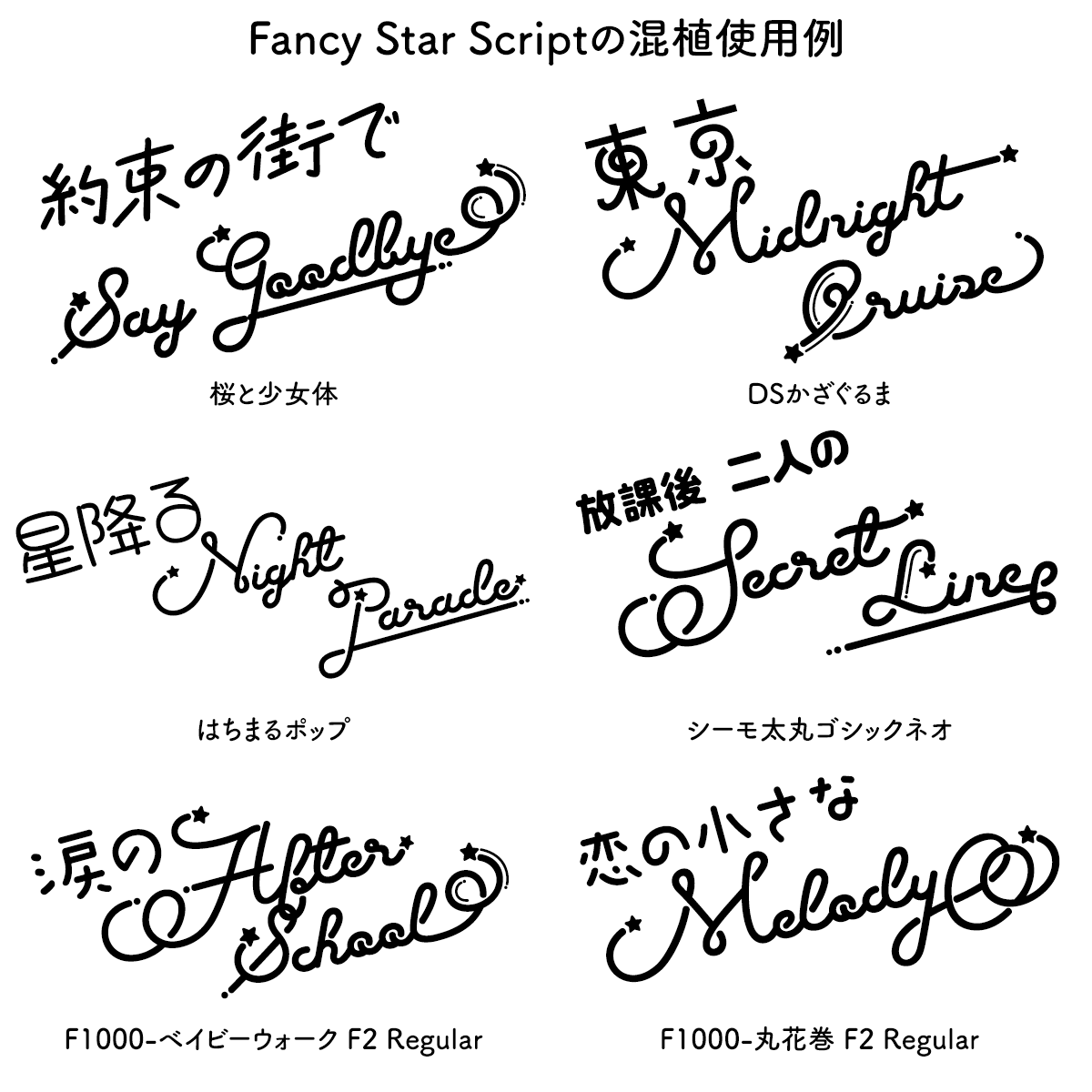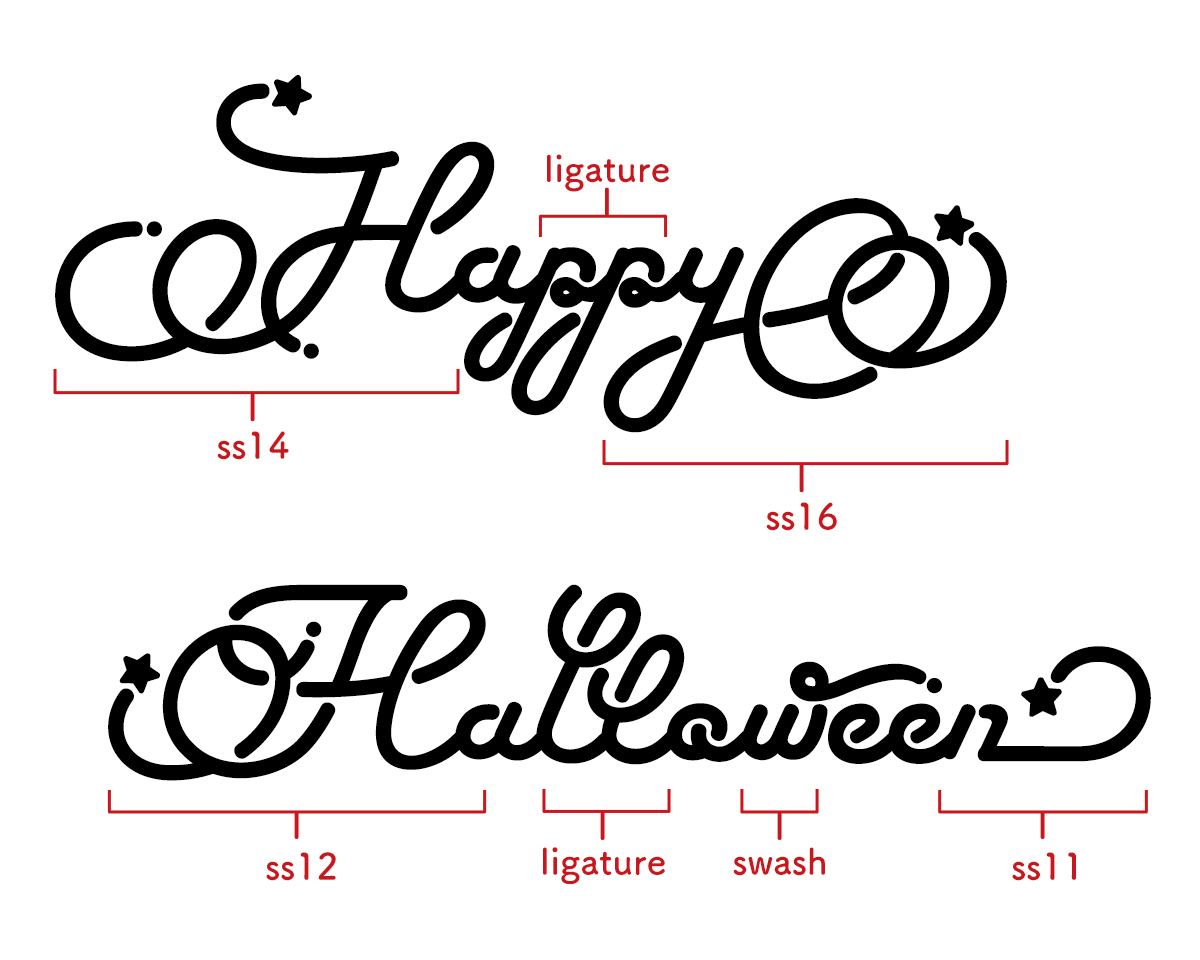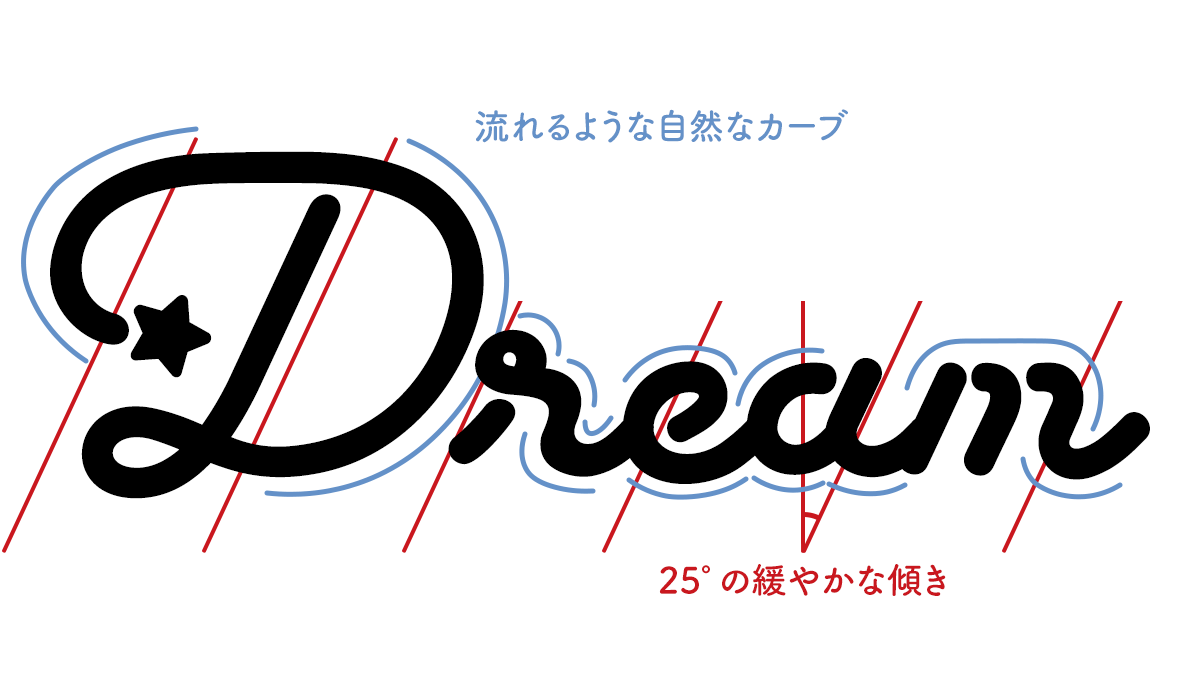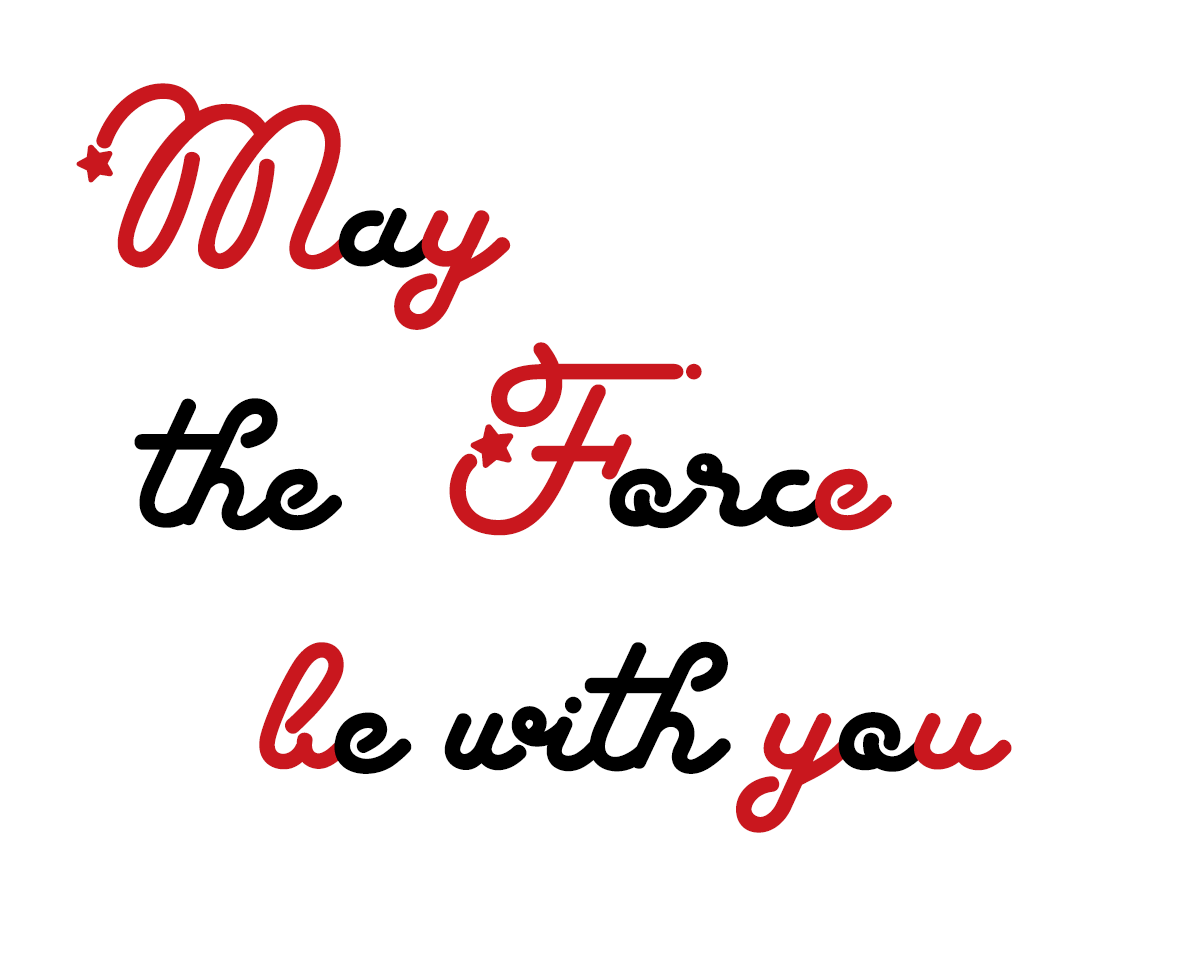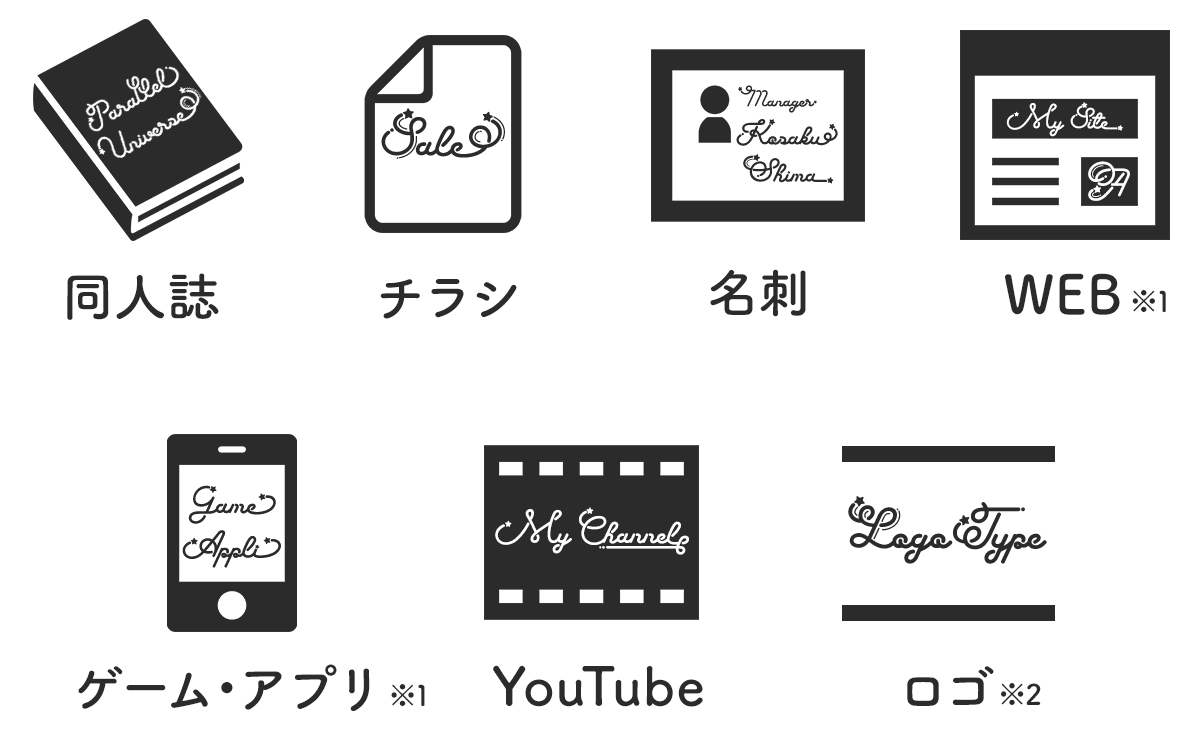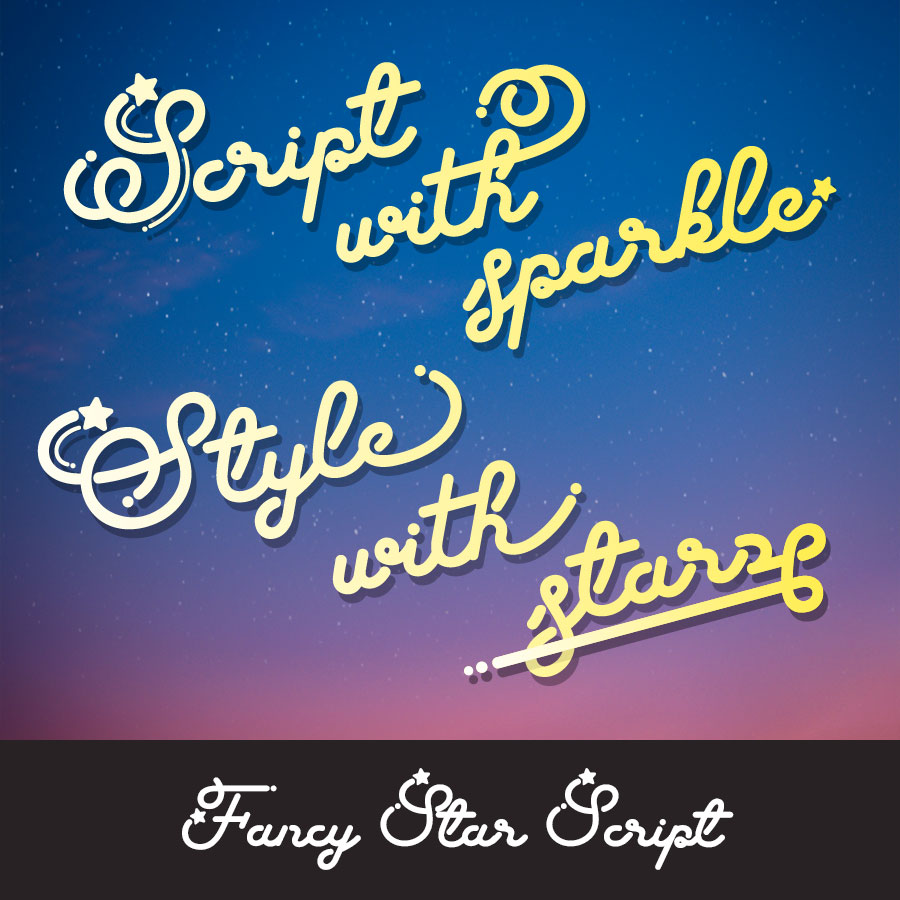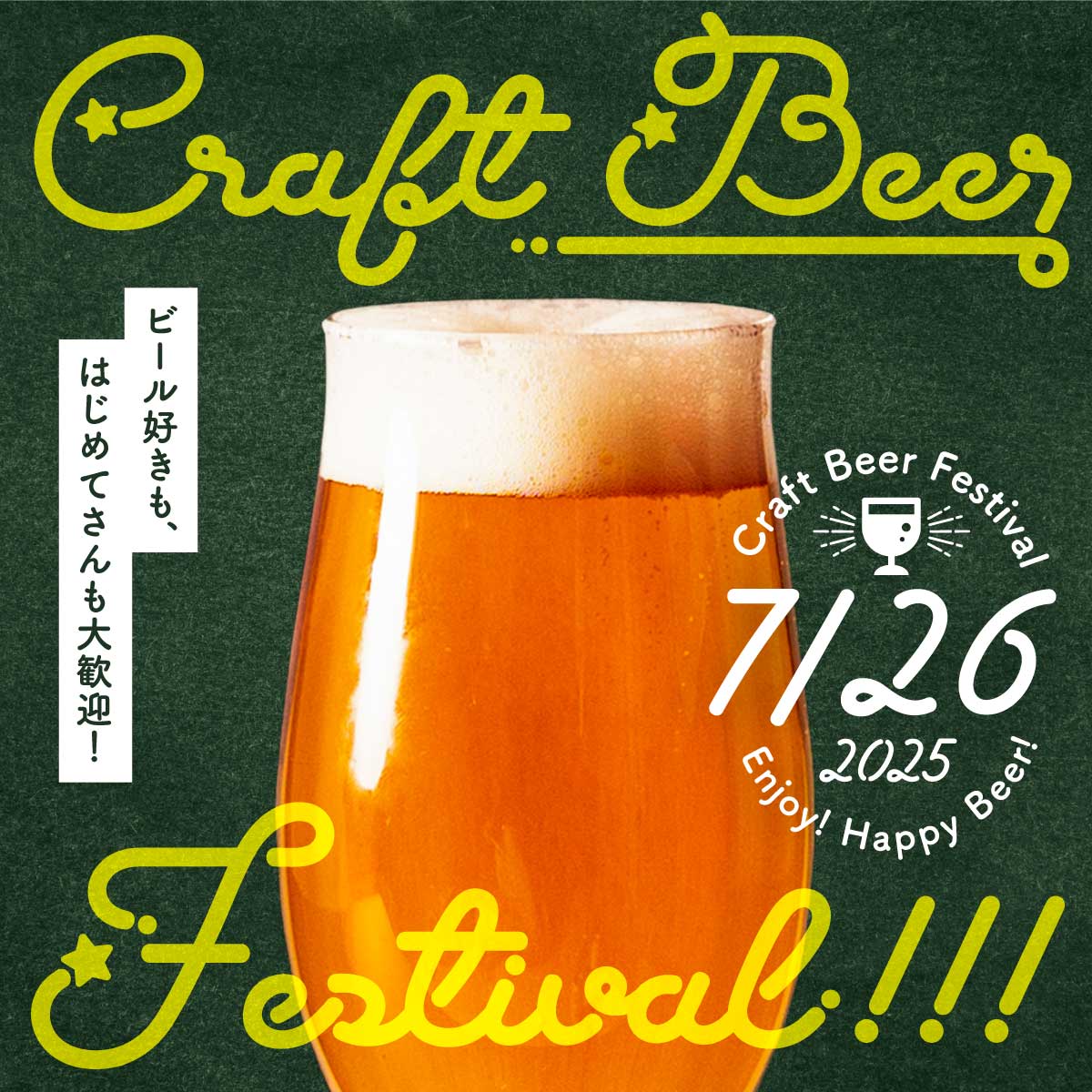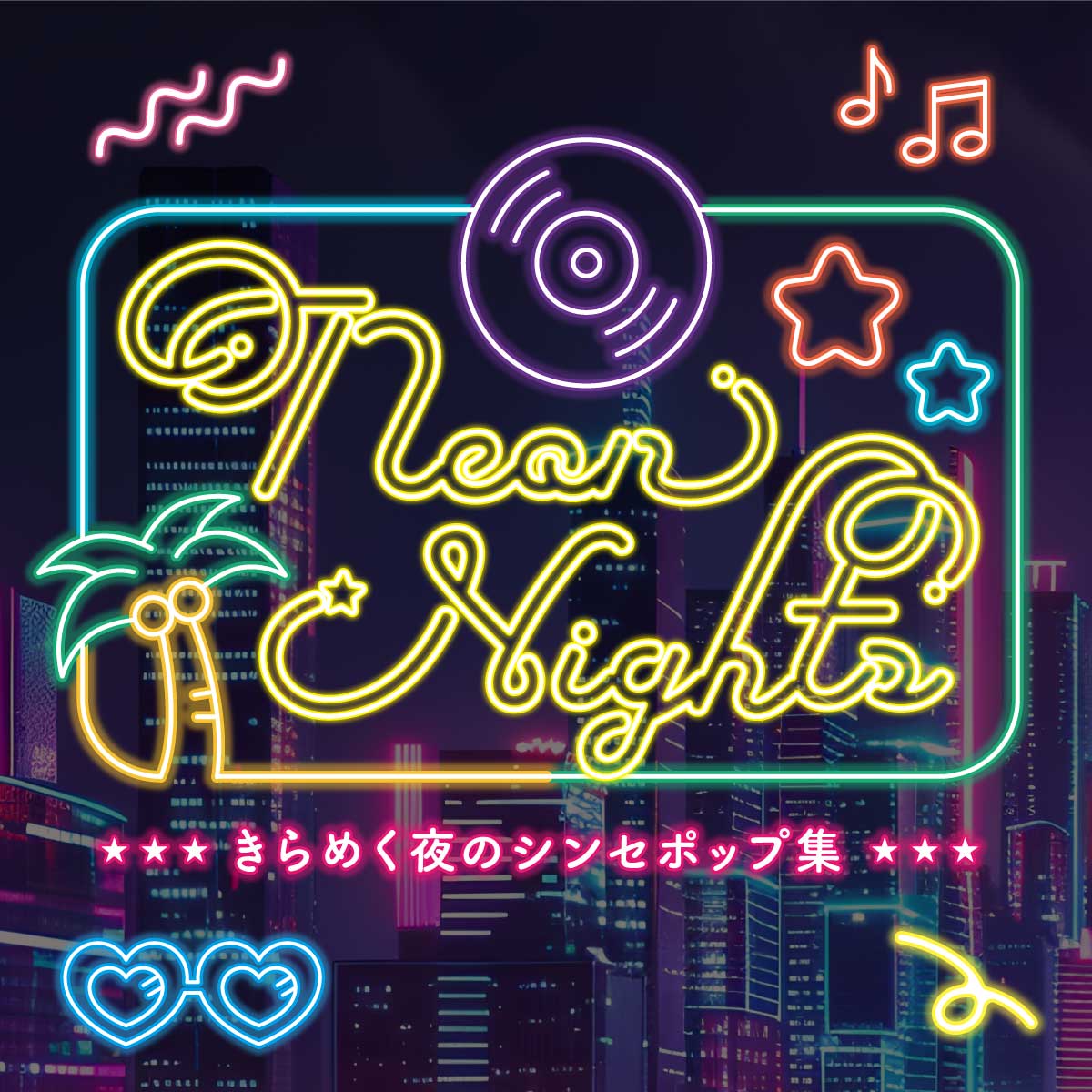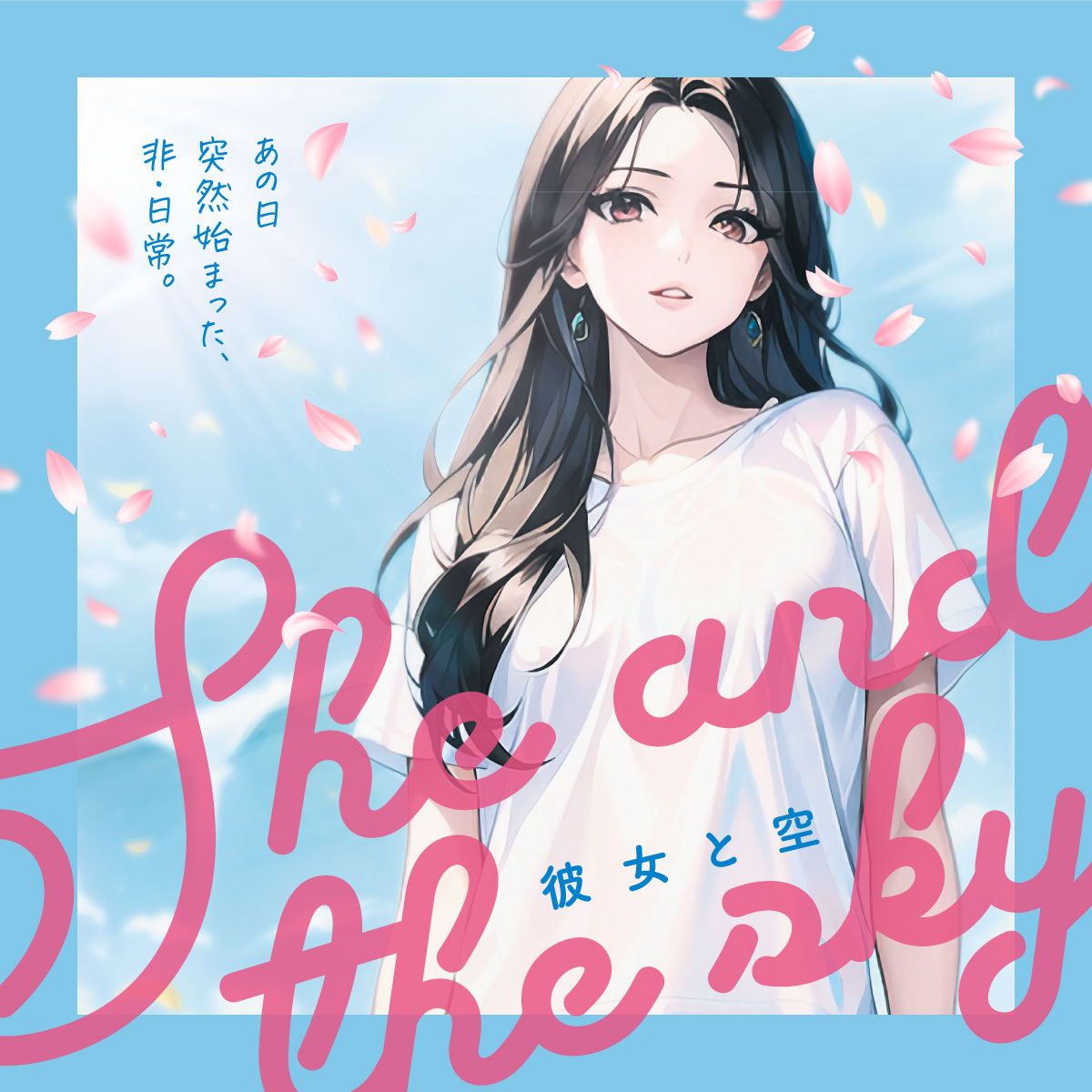
Fancy Star Script シティポップでレトロな筆記体、スクリプト体
シティポップな雰囲気をつくれる筆記体フォント Fancy Star Script|異体字17種類収録
雰囲気のあるデザインを手軽につくりたいときに役立つ筆記体フォントが Fancy Star Script。レトロでポップな印象を持ちつつ、17種類の異体字(異なる文字デザイン)を使い分けることで、ひとつの言葉にもさまざまなニュアンスを加えることができます。
Illustrator や Photoshop では、文字を入力したあとに簡単に異体字へ切り替えることが可能です。また、異体字の切り替え機能がないソフトでも、異体字ごとに用意されたファイルを選ぶだけで使えるので安心です。
ロゴやZINE、MVのタイトルなど、雰囲気を大切にしたい場面にフィットするフォントです。デザインに遊び心を添える、ちょっと特別なスクリプト体。Fancy Star Script、きっとあなたも好きになります。
「Fancy Star Script」の概要
Fancy Star Script
シティポップでレトロな筆記体、スクリプト体 Fancy Star Script サンプル  シティポップでレトロな筆記体、スクリプト体 Fancy Star Script サンプル
「Fancy Star Script」とは?
文字って、もっと自由でいい ──「Fancy Star Script」に込めた遊び心とときめき
シティポップでレトロな筆記体、スクリプト体 Fancy Star Scriptの制作者 渋谷瞳さん
子どもの頃のロゴ遊びから始まり、手書きの温かさとデジタルの設計を融合させて独自のフォントを生み出してきたタイプデザイナー・satsuyakoさん。
そんな彼女が手がけた「Fancy Star Script」は、ノスタルジックでポップ、そして自由なリズムを感じさせる筆記体フォントです。 星のようにきらめく文字たちは、手書きの楽しさと遊び心に満ちていて、ロゴやタイトルを「見る人の記憶に残す」力を秘めています。
この書体に込めた思いや制作背景、こだわりの設計、そして使う人に伝えたいメッセージを伺いました。
「こんなフォントがあったらいいな」という発想から生まれる、シンプルで少し遊び心のあるフォントが特徴。筆記体やピクセル風などジャンルは多彩で、代表作に「Fancy Star Script」や「Love Letter」などがある。
カリグラフィーの経験を活かした繊細なデザインと、日本人ならではの感性が織りなす作風は、多くのクリエイターに支持されている。SNSでは制作過程や使い方のヒントも発信中。
「文字って面白い」──遊び心から始まった、世界に届く文字づくり
シティポップでレトロな筆記体、スクリプト体 Fancy Star Scriptの作者 satsuyakoさんの創作のルーツ
フォントとの出会いは、子どもの頃の”ロゴ遊び”から
フォントに興味を持ち始めたのは、小学生の頃に好きなフォントを使ってロゴのようなものを作って遊んでいたことがきっかけでした。
画面の中で文字が持つ雰囲気や印象の違いに夢中になって、そのとき目に留まったフォントの存在はいまも記憶に残っています。
デザインの仕事を通して”つくる”楽しさに目覚めて
学生時代からデザイン制作会社の仕事に携わるようになり、当時は携帯電話向けの「デコメ」素材などの制作が主な業務でした。
その延長でドット系のフォントを作るようになり、漢字入りの日本語フォントがまだ少なかったこともあって、まずは自分の手書き風の文字で作ってみようと思ったのが、本格的にフォント制作をはじめたきっかけとなりました。
世界に届く文字づくりを目指して
その後、日本国内で配布・販売されている筆記体フォントの少なさにも気づき、欧文フォントの制作にも自然と関心が広がっていきました。
筆記体らしさを追求するなかで、カリグラフィーの歴史や書法も独学で少しずつ学びながら制作に取り組んでいます。
また、初期に制作した日本語フォントの一部が思いがけずGoogle Fontsに採用されたことをきっかけに、より多くの方に届けられる文字づくりを意識するようになりました。
フォントを制作する中で、先に道を切り拓いてこられた多くの書体や制作者の存在に触れるたび、その緻密さや美しさに心を動かされ、今も変わらず大きな刺激と励みをもらっています。
初期作から広がる世界──「自分の文字」をフォントにするまで
Satsuyakoさん 最初に制作したフォント「ゆるもじ」
最初に制作したフォント「ゆるもじ」
一番最初に作ったのは、2012年ごろに制作したピクセル風フォントの「ゆるもじ」です。
当時、かわいいドット絵を描いて個人サイトで公開することが流行っていた時代で、お仕事でもドットでよくこういう字を描いていました。
Satsuyakoさん 初めて作った手書き風「よもぎフォント」
初めて作った手書き風「よもぎフォント」
同じような作風として「よもぎフォント」という手書き風の日本語フォントも作りました。
よもぎフォントは学生時代に実際に書いていた手書きの字をベースにしたもので、軽いノリで作り始めたものでしたが、6000文字以上もの漢字を含めた日本語フォントを作る大変さを思い知ったフォントです…。
Satsuyakoさん 今でも人気のかなフォント 「Cherry Bomb」
今でも人気のかなフォント 「Cherry Bomb」
同時期に作ったものに「Cherry Bomb」というフォントがあります。
このフォントは私が中学生のときにイラストなどに必ず添えていた字体で、いつかフォント化してみたいなーと考えていたものです。
フォントを作れるようになったことが嬉しくて勢いで作ってしまったフォントでしたが、太めのポップなフォントはあらゆる場面で使いやすいようで、「Cherry Bomb One」と改名された今も街中のポスターや看板、誌面などでふと見かけることがあり、作り手としても嬉しく感じています。
「Fancy Star Script」に込めた、ときめきと筆跡のリズム
シティポップでレトロな筆記体、スクリプト体 Fancy Star Script こだわっているポイント きらきらとした星のモチーフとネオンサインのようなテイストを掛け合わせ
“流れ星の筆記体”にノスタルジックなときめきを添えて
「Fancy Star Script」は、”流れ星の筆記体”というロマンチックなコンセプトをもとに、きらきらとした星のモチーフと、ネオンサインのようなテイストを掛け合わせた、ノスタルジックでとびきりキュートな英字フォントです。
ひと文字ずつにポップなかわいさと哀愁を感じさせる、夢みたいな「ときめき」を閉じ込めています。
見た人の心に残るロゴやタイトルに、「かわいい」を届けるお手伝いができたら嬉しいです。
シティポップでレトロな筆記体、スクリプト体 Fancy Star Script こだわっているポイント 「夢の中のようなキラキラ感」と「自由でリズミカルな筆致」
星の軌跡のようなリズムを筆跡にのせて
このフォントでは「夢の中のようなキラキラ感」と「自由でリズミカルな筆致」を大事にしました。
流れ星の軌跡を表現した二重線やループをあしらった大文字、なめらかに繋がる小文字、どれも装飾過多になりすぎないように調整しつつ、手書きのような温かみや躍動感が残るように設計しています。
タイトルにも使いやすいよう、少し太めのモノラインでポップな雰囲気に仕上げています。
シティポップでレトロな筆記体、スクリプト体 Fancy Star Script こだわっているポイント 大文字14種類、小文字17種類の異体字
字形を自由にカスタムできる楽しいフォント
特に、異体字のバリエーションにこだわっています。デフォルトの字形に加え、大文字14種類、小文字17種類の異体字を備えています。
字形パネルやOpenType機能を使えば、文字ごとに違った表現が楽しめる「使い手の遊び心」に応える設計です。
“かわいい”と“使いやすい”を両立させて、次の一歩へ
”かわいい”と”使いやすい”のどちらも大切に、新しい書体を開発中 ”かわいい”と”使いやすい”のどちらも大切に、新しい書体を開発中
自分の”ときめき”から生まれるフォント
今後も、自分自身が「使ってみたい!」と感じるフォントを、ひとつずつ丁寧に形にしていきたいと思っています。
カリグラフィーや万年筆での手書き練習も毎日続けながら、より滑らかで表情豊かなフォントが作れるよう挑戦中です。
”かわいい”と”使いやすい”のどちらも大切に
今は星やハート、リボンなど、自分が好きなモチーフを取り入れて、ひと目で「かわいい!」と思ってもらえることを意識しながら、使う人にとっても扱いやすいフォントを目指しています。
時折、「はじめて有料フォントを買いたくなった」と言っていただけることもあり、誰かの”フォントに触れるきっかけ”になれたことが大きな励みになっています。
これからも自分の作風を大切に、オリジナルなフォントの世界観を追求していきたいです。
誰が使っても”きれい”に見えるフォントを
誰が使っても自然にきれいに見えることの難しさも、日々痛感しています。
フォントの構造や設計、使われ方を研究しながら、今後はより汎用性と魅力を両立したフォントを目指していきたいです。
海外の高品質な欧文フォントに刺激を受けつつ、日本人の感性に寄り添う、見ているだけで楽しくなるフォントを、これからも形にしていきたいです。
ちなみにFancy Star Scriptは太字バージョンを開発予定です。
現在開発中のFancy Star Scriptは太字バージョン
「Fancy Star Script」の特徴
見た目の美しさだけでなく、意味や印象まで左右するのが、文字のかたち。
Fancy Star Script は、細かい部分まで丁寧に設計された筆記体フォントです。
ここでは「なぜこのフォントが雰囲気をつくれるのか?」を、3つの視点から紹介します。
一文字に、いろんな表情を。異体字の楽しさ
Fancy Star Script シティポップでレトロな筆記体、スクリプト体 一文字に、いろんな表情を。異体字の楽しさ
同じ文字でも、スタイルの違うデザイン(異体字)が複数用意されています。
文字の雰囲気を変えたいときに、異体字を選ぶことで自由にアレンジが可能です。
※ 異体字の切り替えに対応していないソフトでも、異体字ごとのファイルが17種類用意されているため、安心して使えます。
なめらかなカーブと、ほどよい傾き
Fancy Star Script シティポップでレトロな筆記体、スクリプト体 なめらかなカーブと、ほどよい傾き
流れ星が流れるような自然なカーブと、緩やかな傾きが特徴です。
スクリプト体らしい動きがありながらも、読みやすさもしっかり考えられています。
語頭や語尾は流れるような装飾
Fancy Star Script シティポップでレトロな筆記体、スクリプト体 語頭や語尾は流れるような装飾。
流れるような装飾を加えた文字も収録。語頭や語尾に少しがあるだけで、ぐっと印象的な仕上がりになります。
「Fancy Star Script」の使用例
Fancy Star Script は、ただの装飾用フォントではありません。心地よいリズム感と、どこか懐かしく都会的なレトロ感を併せ持ち、タイトルやロゴなど“目を引かせたい場所”で真価を発揮します。
文字自体が持つ存在感と柔らかな動きは、シティポップやZINE、MVタイトルなど、世界観を伝えるデザインにぴったり。ひと目見ただけで記憶に残る、そんな印象を生み出せるスクリプト体です。
・同人誌・ZINEの表紙
Fancy Star Script シティポップでレトロな筆記体、スクリプト体 使用例 同人誌・ZINEの表紙
・MVやプレイリストのカバーアート
Fancy Star Script シティポップでレトロな筆記体、スクリプト体 使用例 MVやプレイリストのカバーアート
・イベントや展示会のフライヤー風
Fancy Star Script シティポップでレトロな筆記体、スクリプト体 使用例 イベントや展示会のフライヤー風
・和文フォントとの混植
Fancy Star Script シティポップでレトロな筆記体、スクリプト体 使用例 和文書体とのフォント混植
「Fancy Star Script」の使用許諾
柔軟な使用許諾で、チラシやポスター、商品パッケージ、同人誌などの紙媒体だけでなく、Webサイト、ロゴデザイン、YouTube用の動画や動画広告、プロモーション用動画など、ビジネス・趣味を問わず幅広い用途でお使いいただけます。
※CanvaなどのデザインWebアプリでの使用については別途契約が必要となります。
シティポップでレトロな筆記体、スクリプト体 Fancy Star Script 使用許諾
印刷 Web ゲーム・アプリ 映像 ロゴ
◯ ◯※1 ◯※1 ◯ ◯※2
※1 フォントをサーバーへアップロードする場合は、別途契約が必要
※2 商標登録は別途許諾が必要
「Fancy Star Script」の仕様
Fancy Star Script シティポップでレトロな筆記体、スクリプト体 イメージ
ss1
Fancy Star Script ss1 シティポップでレトロな筆記体、スクリプト体
ss2
Fancy Star Script ss2 シティポップでレトロな筆記体、スクリプト体
ss3
Fancy Star Script ss3 シティポップでレトロな筆記体、スクリプト体
ss4
Fancy Star Script ss4 シティポップでレトロな筆記体、スクリプト体
ss5
Fancy Star Script ss5 シティポップでレトロな筆記体、スクリプト体
ss6
Fancy Star Script ss6 シティポップでレトロな筆記体、スクリプト体
ss7
Fancy Star Script ss7 シティポップでレトロな筆記体、スクリプト体
ss8
Fancy Star Script ss8 シティポップでレトロな筆記体、スクリプト体
ss9
Fancy Star Script ss9 シティポップでレトロな筆記体、スクリプト体
ss10
Fancy Star Script ss10 シティポップでレトロな筆記体、スクリプト体
ss11
Fancy Star Script ss11 シティポップでレトロな筆記体、スクリプト体
ss12
Fancy Star Script ss12 シティポップでレトロな筆記体、スクリプト体
ss13
Fancy Star Script ss13 シティポップでレトロな筆記体、スクリプト体
ss14
Fancy Star Script ss14 シティポップでレトロな筆記体、スクリプト体
ss15
Fancy Star Script ss15 シティポップでレトロな筆記体、スクリプト体
ss16
Fancy Star Script ss16 シティポップでレトロな筆記体、スクリプト体
ss17
Fancy Star Script ss17 シティポップでレトロな筆記体、スクリプト体
ss18
Fancy Star Script ss18 シティポップでレトロな筆記体、スクリプト体